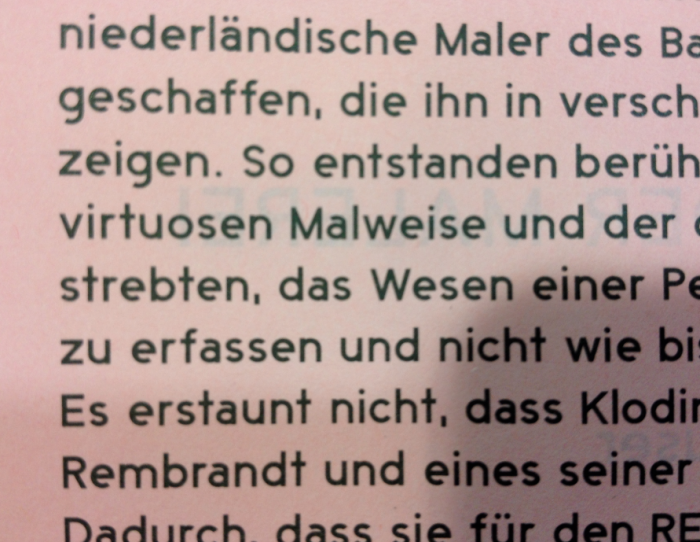
liebe leser,
neuerdings bekam ich diese schrift unter die linsen und konnte in der eile nur ein schlechtes foto davon knipsen.
erst dachte ich, es sei die metric. dazu ist allerdings u.a. der bogen des gemeinen a und e zu wenig stark ausgeprägt …
ich freue mich über zuschrift der analysten.